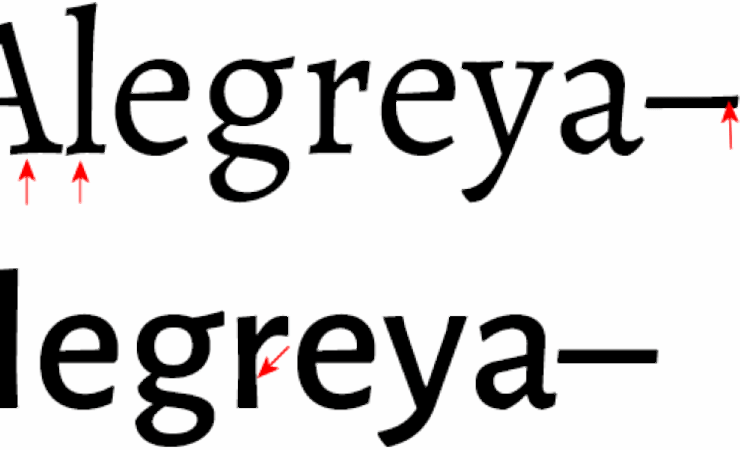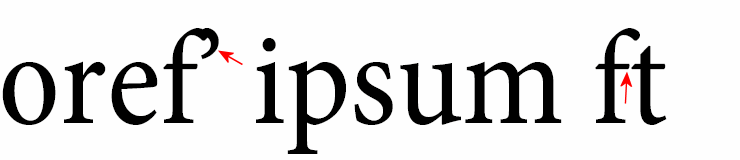
Suche umfangreiche Antiqua- und Grotesk-Schriftfamilie für Langtext
Wie die Überschrift bereits besagt, bitte ich um Rat bzw. Vorschläge. Für einen längeren Text (non fiction in nicht gewerblichem Kontext, soll in gedruckter Form und als .pdf-Download verfügbar sein) suche ich eine Schriftfamilie, die mir sowohl schmale, als auch fette und kursive Schriftschnitte, und das sowohl mit als auch ohne Serifen (für Überschriften, Markierungen, Seitenzahlen usw.) bietet.
Freilich spielt dabei nicht nur die Lesbarkeit, sondern auch der Geschmack (in meinem Falle außerdem der Preis und die leichte Umsetzbarkeit mit handelsüblichen Textverarbeitungs- und Textsatzprogrammen) eine Rolle; doch gewiss können die hiesigen Experten mir mit Meinungen und ihrem besseren Überblick über die Verfügbaren Schriftarten unter die Arme greifen?
Hierzu einige Gedanken und Anmerkungen meinerseits (als Dreiviertellaie in Sachen Typografie bitte ich um Nachsicht, was Begrifflichkeiten angeht):
Schreiben will ich den Text der Einfachheit und Übersichtlichkeit halber mit Word (dies aber auch schon in der vorgesehenen Schriftart, um ein Gefühl für den Text zu entwickeln); die Umsetzung soll per LaTeX erfolgen.
Die fragliche Schrift muss über doppelte und einfache Guillemets verfügen; über den vollen Lateinischen Zeichensatz, soll heißen, einschließlich aller Sonderzeichen insb. für die nordischen Sprachen; und über einen reichhaltigen Vorrat an Ligaturen, bestenfalls einschließlich der heute m.W.n. nur selten gebräuchlichen Ligaturen [tt], [ch], [ck] u.ä.
Persönlich bevorzuge ich (und wurde darin von Testlesern bestärkt) Schriften mit vergleichsweise hoher X-Linie bei eher geringer Breite und Laufweite. Letzteres mag eine seltsame Eigenheit von mir sein, aber ich halte bspw. die schmale Minion Pro Condensed für wesentlich besser lesbar als die reguläre Minion Pro.
Ich würde die Minion Pro auch gerne verwenden, zumal sie den für mich optisch ansprechendsten Kursiv-Schnitt aller Antiquas besitzt, wenn sie denn nur ein Pendant ohne Serifen besäße; was mich gleichwohl stört, sind geringfügige Über- bzw. Unterschneidungen dieser Schriftart, die mit Laienmitteln schlecht zu bereinigen sind. Teils ist der Abstand zwischen den Serifen bei Majuskel-Minuskel-Kombinationen (z.B. ‹Ub›) und bei Minuskeln auf ‹f›, ‹t› usw. so geringfügig, dass meiner Ansicht nach der Eindruck einer «beschädigten» Ligatur erweckt wird. Außerdem ragt ein Apostroph regelmäßig in «lange» Minuskeln wie eben ‹f› hinein.
Insgesamt gefällt mir die Schrift Alegreya sehr gut — trotz ihrer recht wuchtigen Erscheinung und größeren Laufweite —, und das nicht nur, weil sie einmal mit und einmal ohne Serifen daherkommt. Auch der optische Stil der Schrift spricht mich an, ein schönes Mittel aus einer ernsten, knöchernen Schriftart wie der Times einerseits und andererseits den etwas leichteren Antiqua-Spielarten der Moderne. Etwas in der Art suche ich!
Leider ist die Alegreya für meinen Geschmack allzu verspielt geraten. Die Serifen sind recht konkav gehalten, und das auch noch ungleichmäßig, und selbst die einzelnen Glyphen und Zeichen weisen unterschiedliche Dicke auf. Obwohl es schön ist, wenn eine Schriftart die handwerkliche Herkunft aller Schriftarten nicht verleugnet, ermüdet das doch auf Dauer.
(Hier hat die Dateiqualität durch die Kompression gelitten.)
Nur damit die Minion nicht fälschlicherweise aussortiert wird: Die beschriebenen Kollisionen treten nur auf, wenn das Kerning der Schrift deaktiviert ist (in Word leider standardmäßig; unter Schriftart / Erweitert ein Häkchen bei Unterschneidung setzen, dann sollte es besser aussehen).* Die anderen Stellen wie "ft" würden mich persönlich nicht abhalten, eine ansonsten (aus Deiner Sicht) geeignete und schöne Schrift zu benutzen.
Und was die Serifenlose angeht: Mit der Minion lassen sich auch andere Schriften gut mischen. Hier im Forum gibt's dazu schon Diskussionsfäden.
* Was in der Minion tatsächlich ein Problem ist, sind die extremen Unterschneidungen bei „diesen“ Anführungszeichen. Da Du aber offenbar französische Anführungszeichen verwenden möchtest, sollte dies kein Problem sein.
Danke schon einmal für diesen Hinweis. Und ich dachte, die Unterschneidung sei standardmäßig aktiviert…!
Die Verbesserung ist zwar nur geringfügig, aber immerhin sichtbar.
Was die Kombination mit einer anderen Sans Serif angeht, einen Themenstrang im Forum hatte ich dazu bereits durchsucht, war aber von den dortigen Vorschlägen nicht allzu überzeugt. Man mag es ruhig pedantisch nennen — vermutlich ist es das auch —, aber meines Erachtens nach sticht die fehlende «Verwandtschaft» durchaus ins Auge. Erschwerend kommt hinzu, dass (sollte ich mich für eine nicht frei verfügbare Familie entscheiden) die Serifenlose bei manchen Anbietern bereits kostenlos oder für einen geringen Aufschlag enthalten ist. Das würde ich ggf. gerne ausnutzen.
Unlängst hatte ich einige Heyne-Romane in der Hand, die zu meiner Überraschung in, wenn ich mich nicht irre, Strayhorn gesetzt waren. Gewiss steckt hinter diesen Schriften ein hoher künstlerischer Wert und auch eine Aussage, allerdings geht es mir regelmäßig so, dass ich mir nach einer Viertelstunde die Augen reibe.